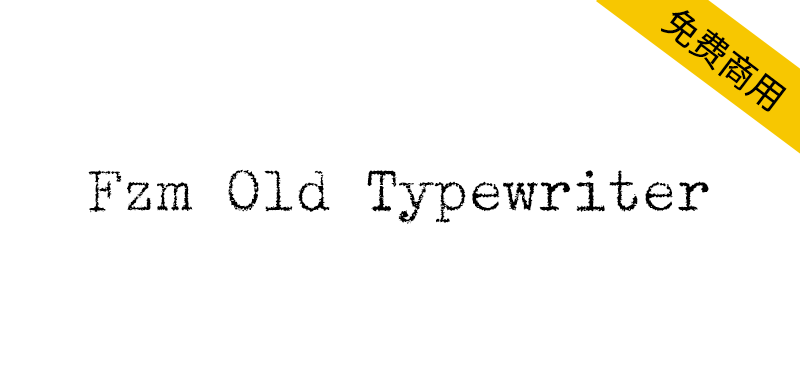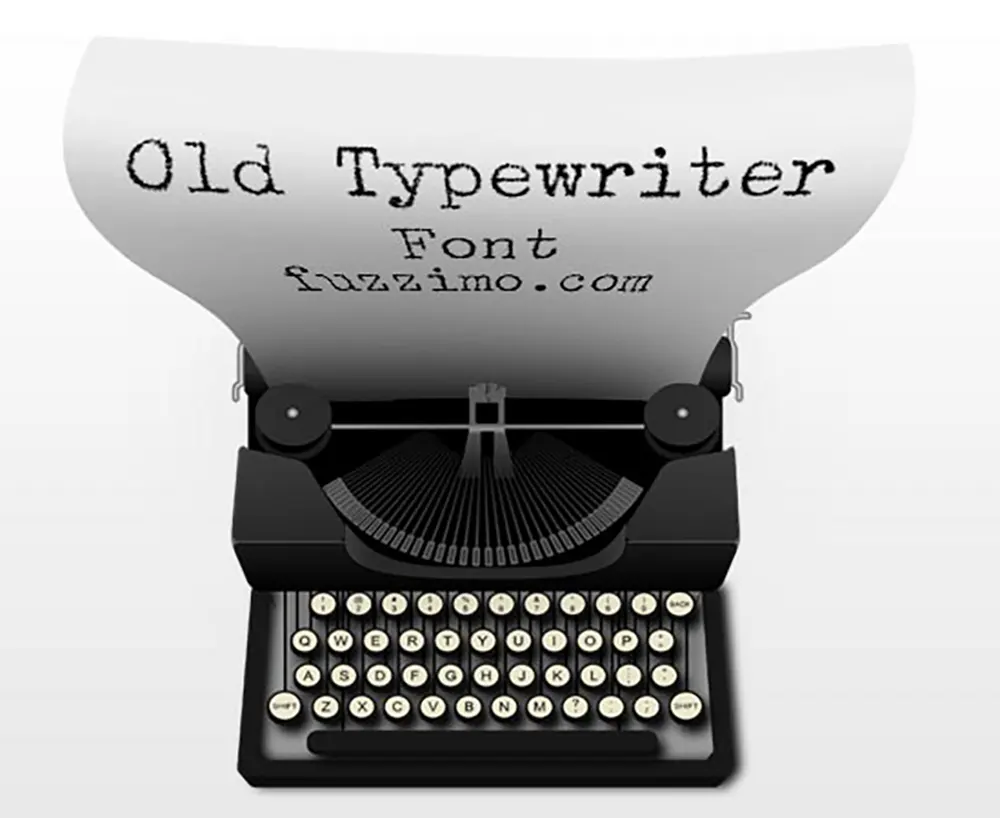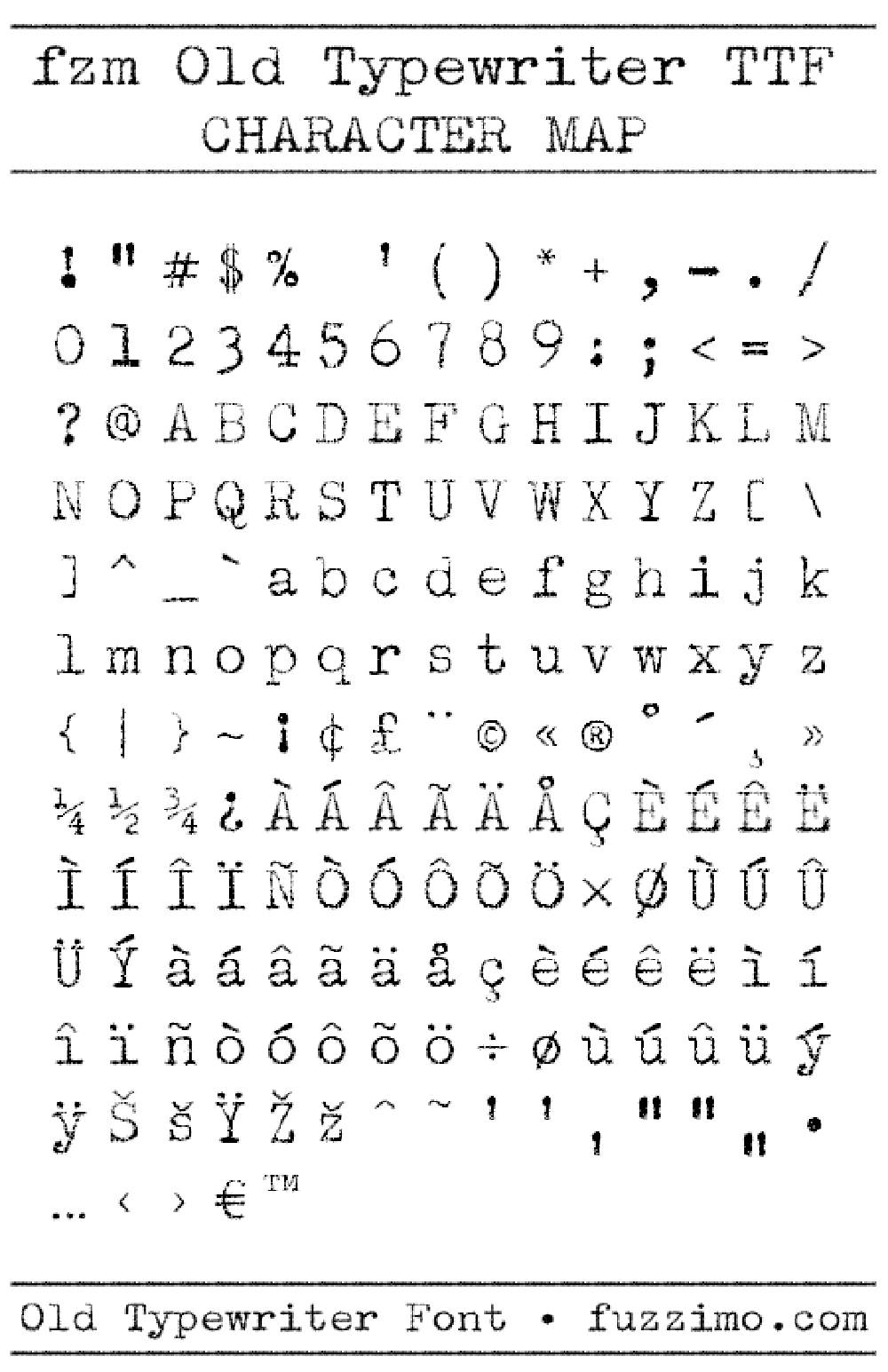
【Fzm Old Typewriter】充满文艺复古感的老式打字机风格字体
Fzm Old Typewriter 是一款充满文艺复古感的老式打字机风格的免费商用英文字体,设计师“Fuzzimo”偶然发现了一封旧信件,很喜欢上面的字体,就扫描了它并提取出所有能用的字母进行修补设计,便形成了这款字体。没有明显的油墨扩散,笔画斑驳磨损感较明显,字体非常干净有秩序,很适合文艺清新的主题。